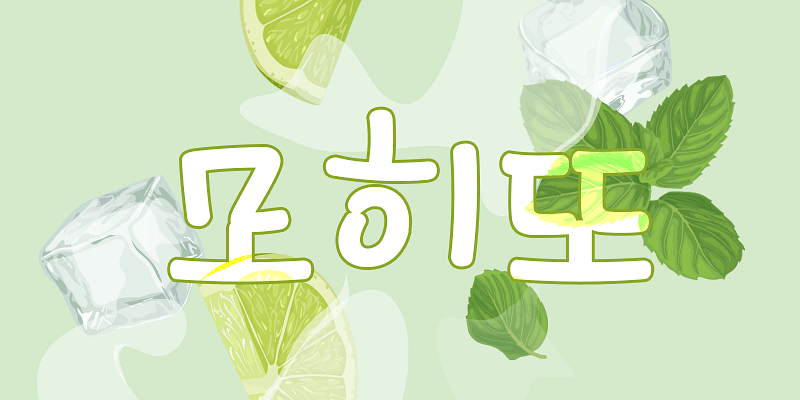
Sandoll Mojito est une police de script arrondie et sophistiquée. La police traduit la naïveté et la candeur qui émanent de l’écriture d’un jeune enfant, par conséquent elle conviendra pour exprimer vos émotions dans des espaces virtuels comme SNS.